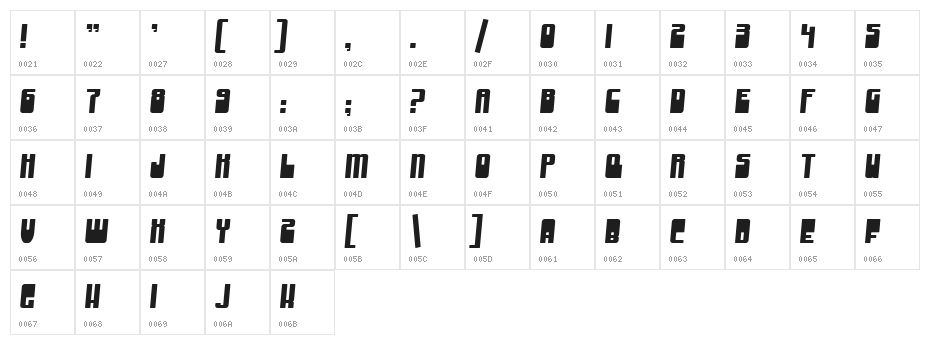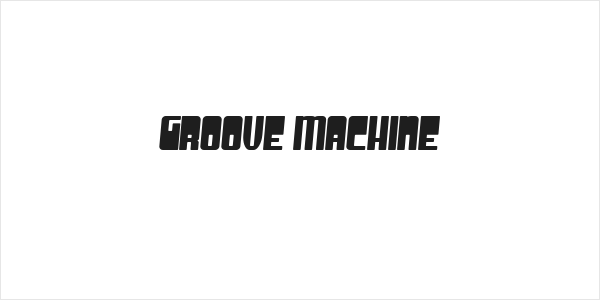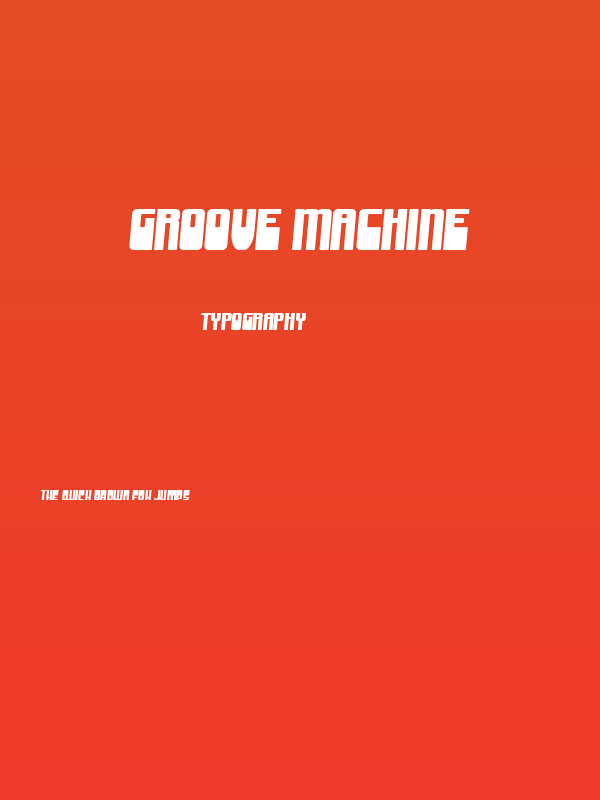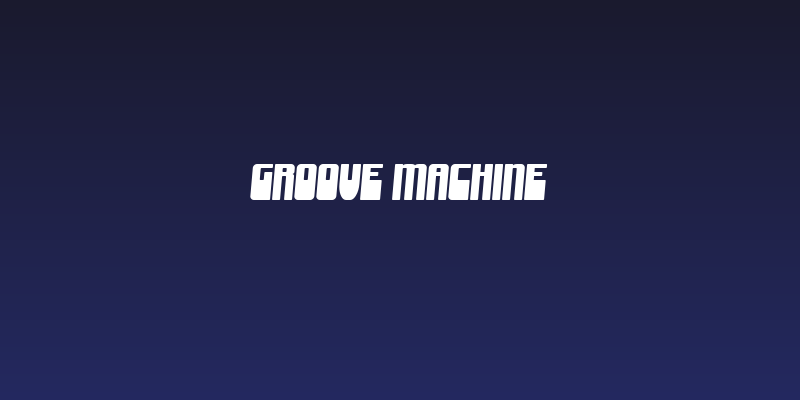
Groove Machine Font
| Ancho | Expanded |
| Proyectos propuestos | Ideal for technology branding, music album covers, sports team logos, and modern advertising campaigns. |